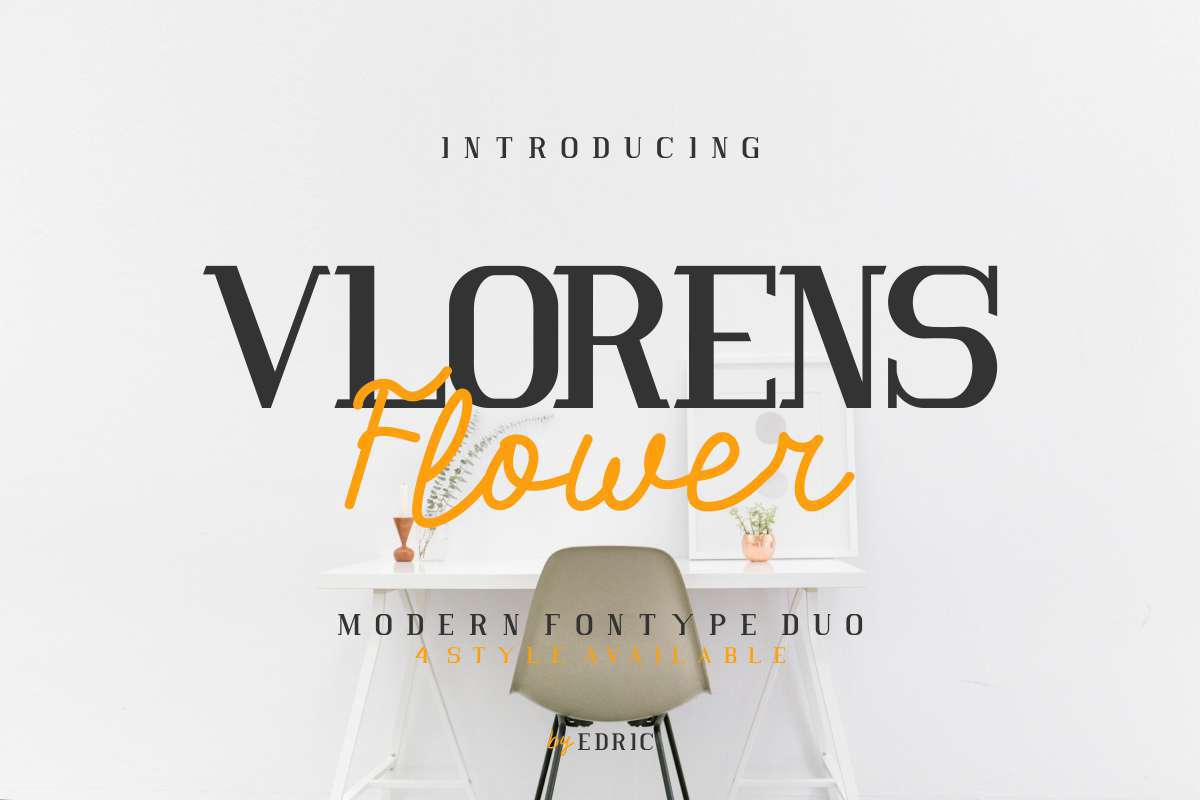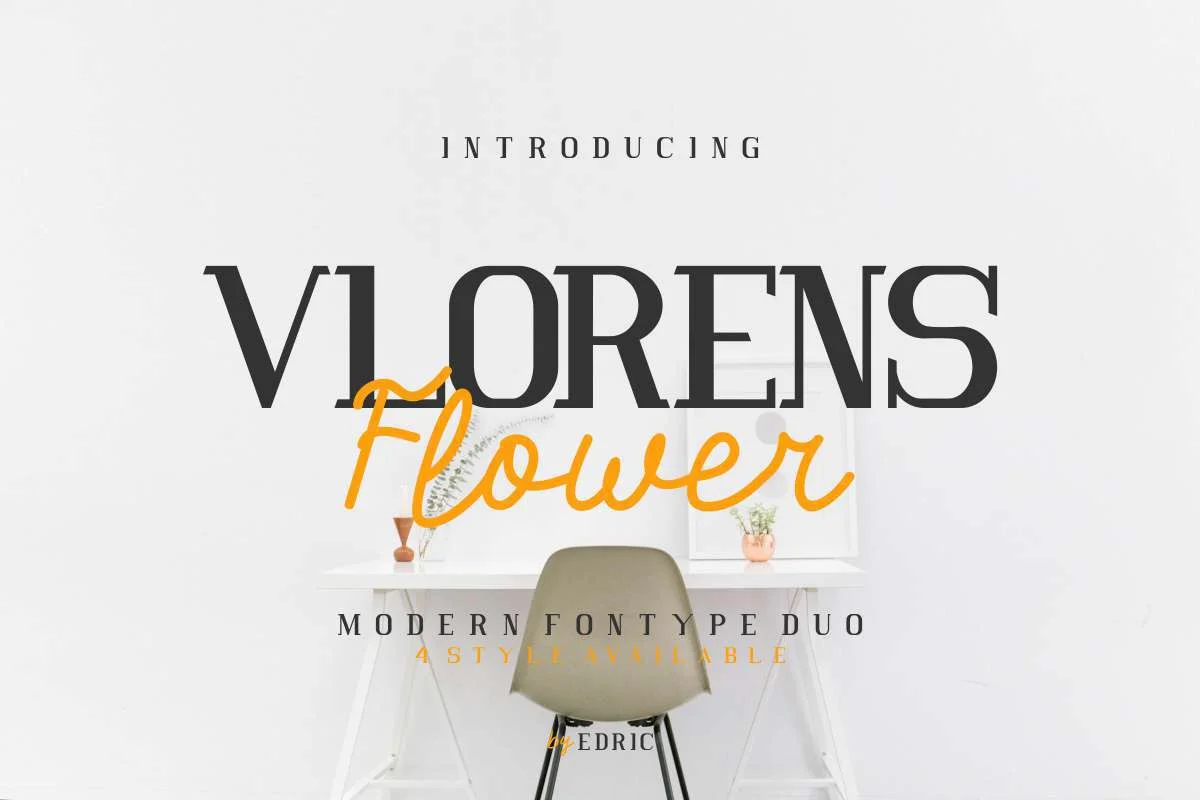
[Fontbundles] Vlorens Flower Font (2022)
Название: Vlorens Flower Font (2022)
Представляем вам наш новый шрифт : Vlorens Flower! Это новое семейство шрифтов, состоящее из : Reguler Serif Display, Stencil, Script и Outline.
Это ЧЕТЫРЕ шрифта в одном семействе. Это современный и стильный шрифт